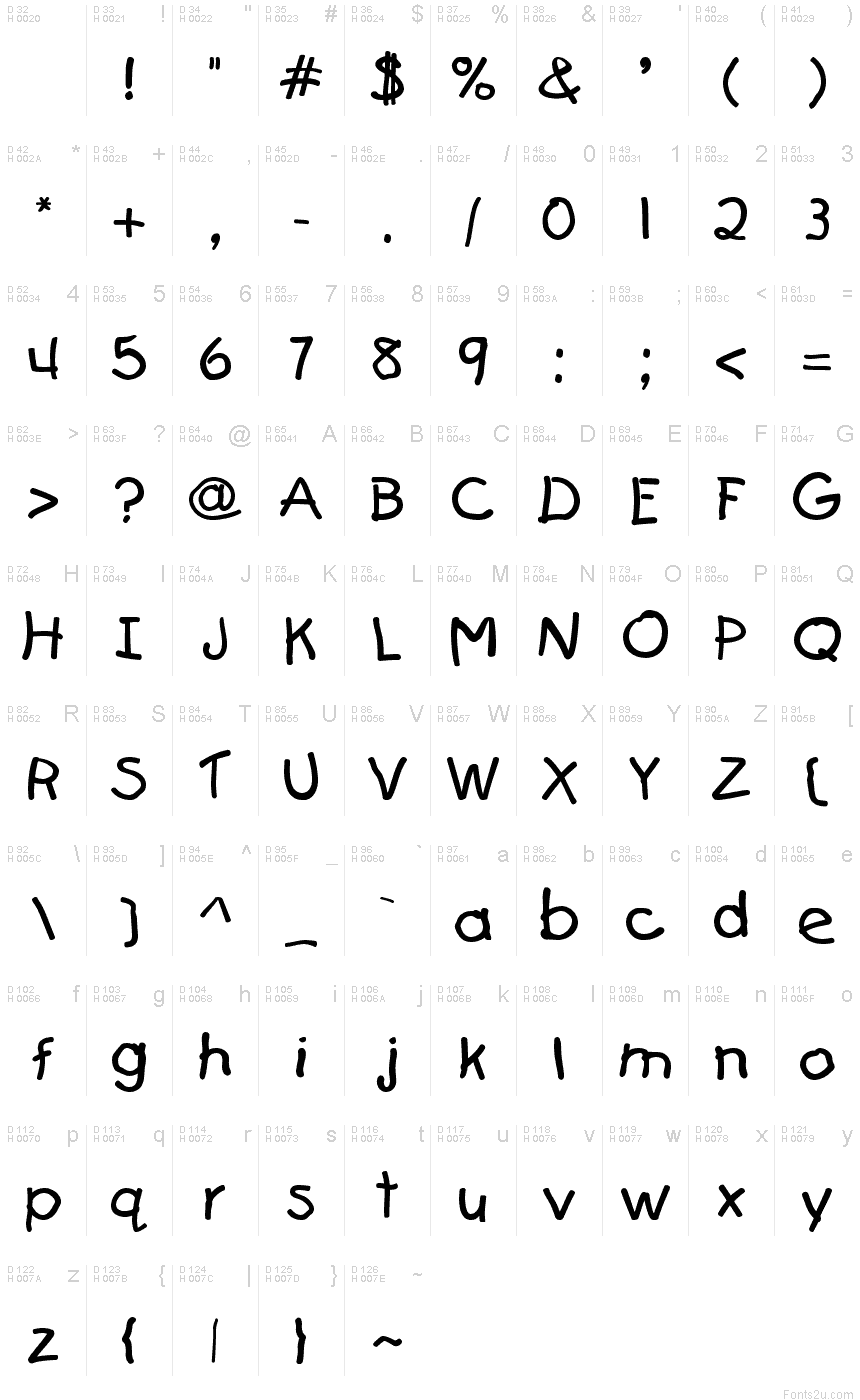
خط Kids من Corel Corporation هو خط عرض مجاني بخط اليد يتميز بالأشكال الحرة وغير المنتظمة لكتابة الفصول الدراسية. الضربات العريضة، والوصلات الدائرية، وارتفاعات الحروف المتغيرة تجعل الكتابة تبدو وكأنها مرسومة بقلم عريض.
وهو يخاطب مباشرة الأطفال والآباء والمعلمين. تلك الجودة المدرسية المألوفة تناسب كتب الأنشطة، وملصقات الفصول الدراسية، والألعاب التعليمية، حيث يدعم الخط بيئة مريحة ومتاحة. ويمكنه أيضاً أن يضفي دفئاً مصنوعاً يدويًا على تغليف الألعاب ورسومات فعاليات الأطفال.